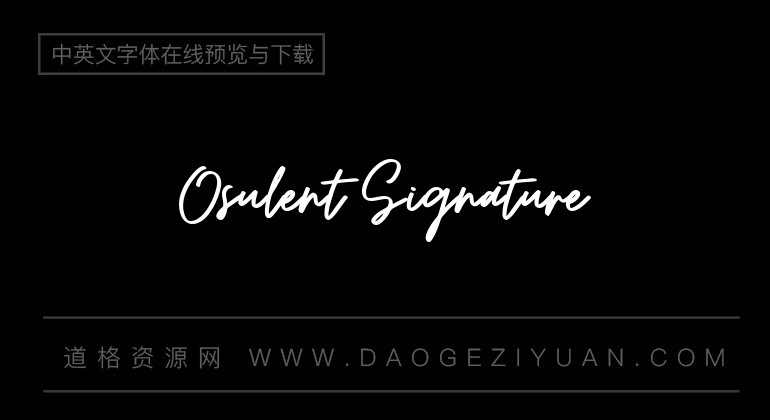
Osulent Signature
Osulent Signature是一款具有现代感的手写体字体,具有轻松愉悦的外观,是一款适合用于品牌标识、海报、标题等的设计元素。它采用自然的笔触,具有流畅的连贯性,可以营造出轻松愉快的氛围,使设计元素更加精致。它也具有多种字重,可以根据设计需求进行调整,以便更好地表达设计意图。
Osulent Signature是一款非常不错的手写艺术字体,具有很好的视觉感,适合于文化类的宣传设计、商业类品牌的广告和产品包装设计以及个性化文字排版等较多场景。